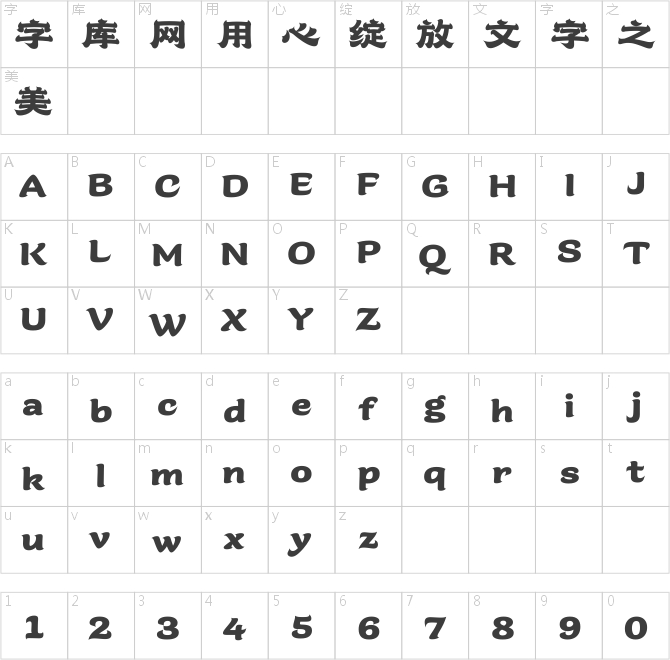
漢儀赤云隸
漢儀赤云隸介紹
漢儀赤云隸是由知名設計師行行珂與漢儀字庫合作打造的一款帶有隸書韻味的設計字體。這款字體運用現代設計語言,在隸書的基礎上改造創新,給予了傳統字體新的生命力。
漢儀赤云隸曾入選Award360°年度設計100、《第十四屆亞太設計年鑒》、《Design360°n.84#特刊#》和《字賦不凡2》。